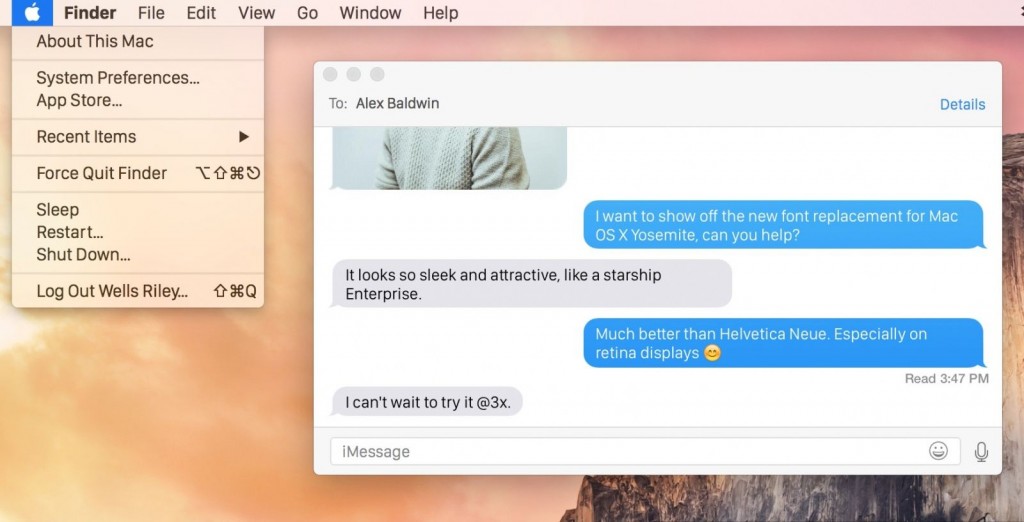
Una piccola guida che spiega come rendere predefinito su OS X il font Apple Watch, di default sul nuovo smartwatch in arrivo. Condivisi da Cult Of Mac, di seguito riportiamo i passaggi da eseguire per far sì che su OS X venga scelto il nuovo font San Francisco ideato da Apple per il proprio smartwatch in arrivo sul mercato entro i primi mesi del 2015.